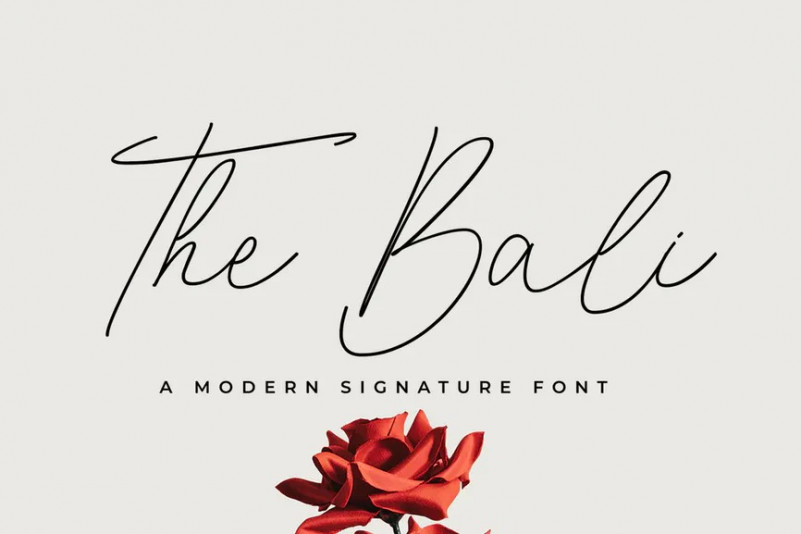
The Bali Font
Le Bali est une écriture manuscrite attrayante, idéale pour une utilisation dans des projets qui ont besoin d’un style organique et naturel. Cette police est idéale pour Logo, logo, image de marque, mariage, mode, étiquette, couverture de livre, t-shirt, poste Instagram, etc., et peut ajouter un look élégant et élégant à votre travail.